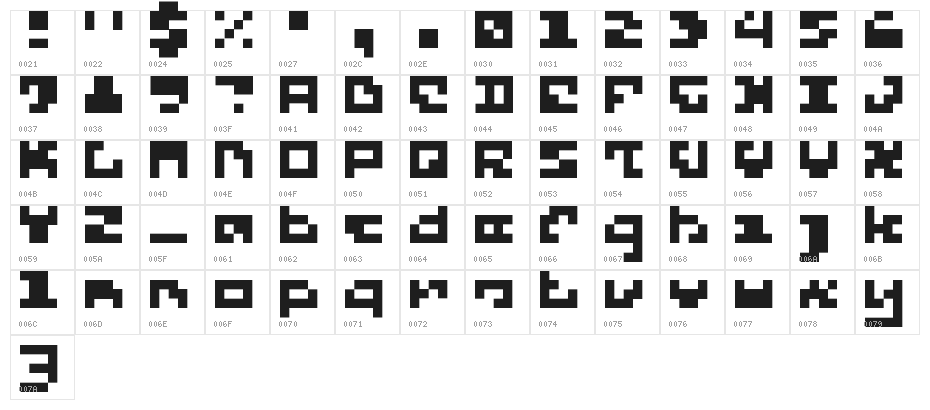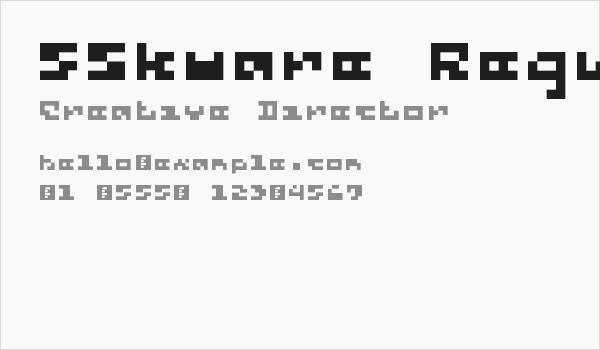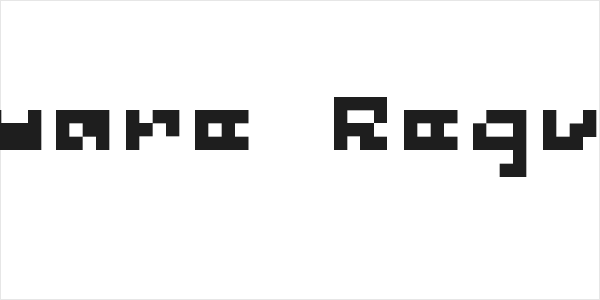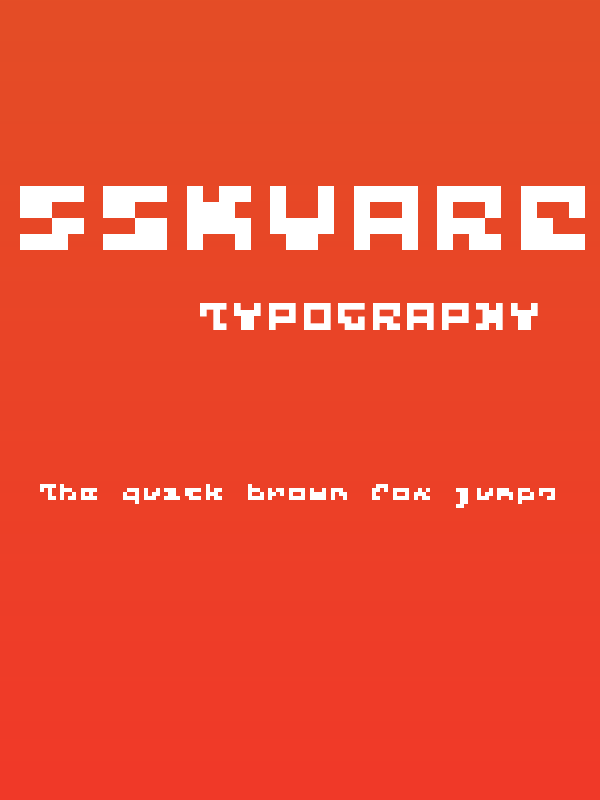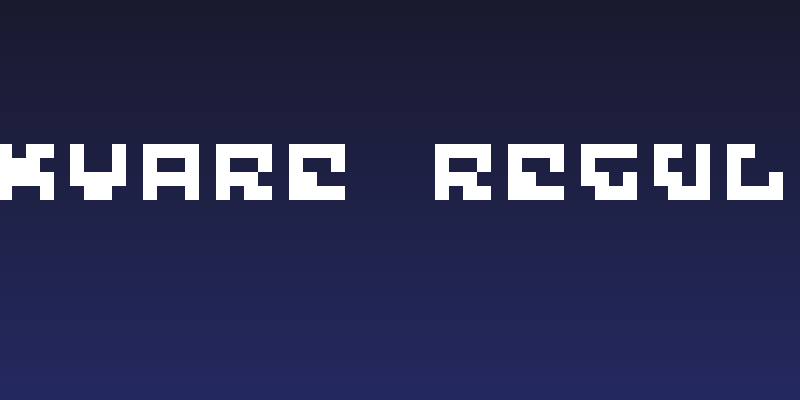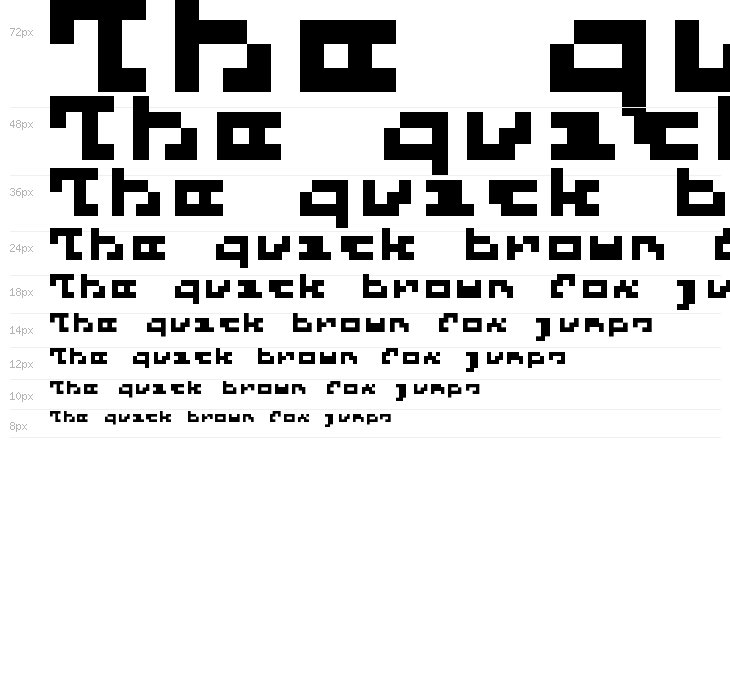
5Skware Regular Font
| Stil general | Modern, Vintage |
| Caz de utilizare | Logos, Headlines, Digital displays |
| Proiecte propuse | Ideal for video game graphics, tech-themed posters, digital art, and retro-style branding. |